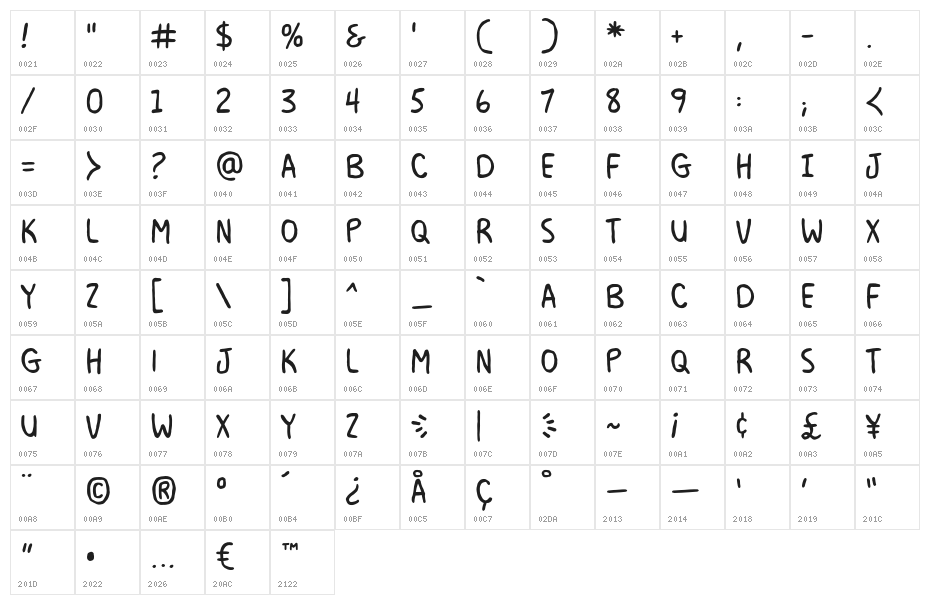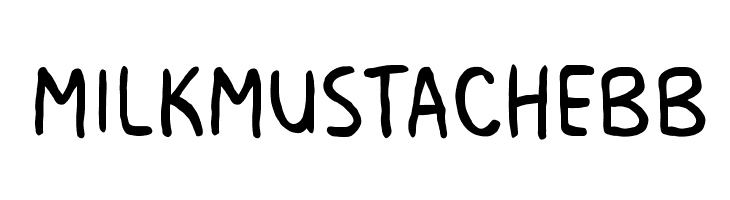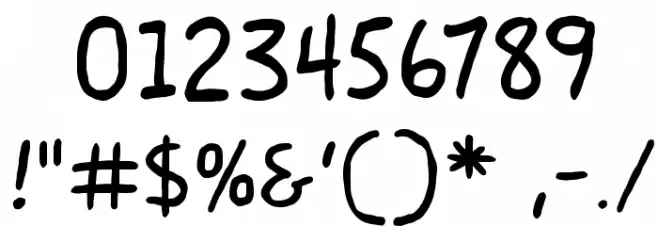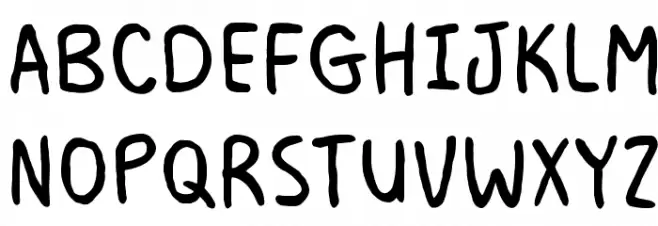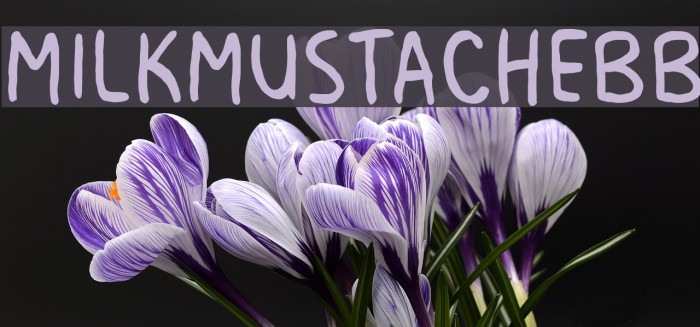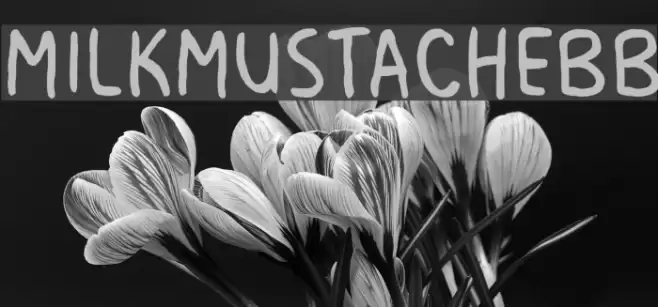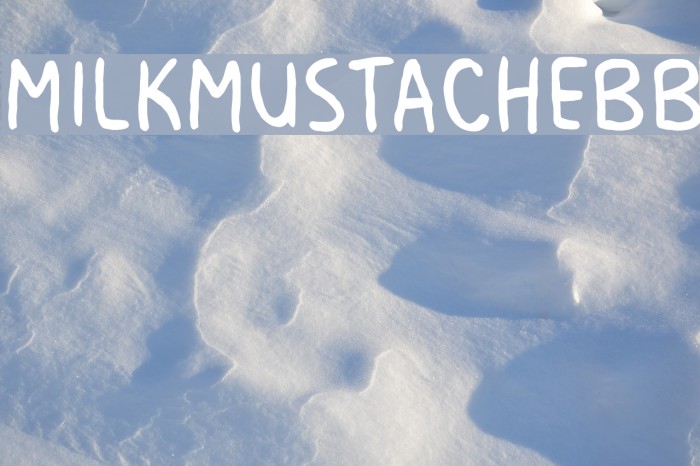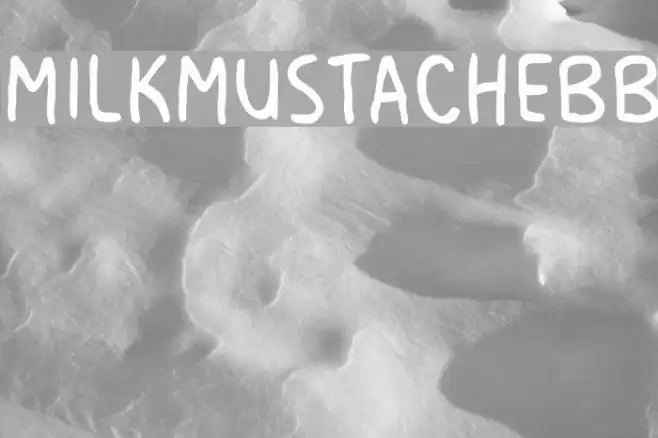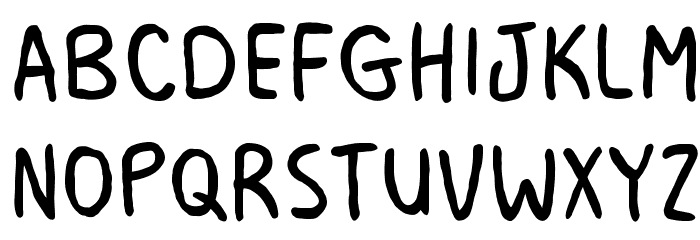
MilkMustacheBB Font
| Общий стиль | Whimsical |
| Область применения | Headlines, Logos, Informal Text |
| Рекомендуемые проекты | Ideal for children's books, greeting cards, playful branding, and informal invitations. |